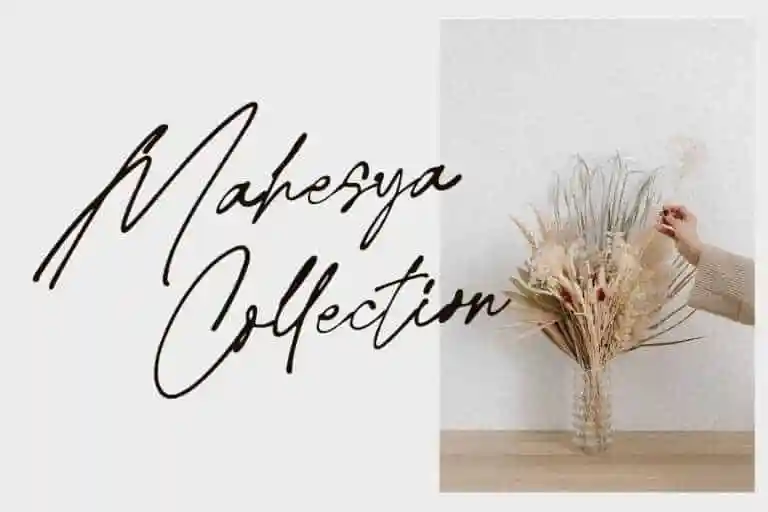
Belandia Signature Script Font – Download Grátis
A Belandia Signature Script Font é uma elegante tipografia escrita a mão que traz uma sensação natural e envolvente para qualquer projeto. Esta fonte perfeita tanto para assinaturas quanto para design de marca, logotipos e materiais promocionais, oferece um toque sofisticado aos seus trabalhos. Suas curvas fluidas e detalhes delicados são ideais para criar mensagens impactantes em estilos como postagem, web design e impressões publicitárias. Com uma aparência que não só combina bem com designs modernos, mas também oferece um toque clássico aos elementos mais tradicionais de seu trabalho. A Belandia Signature Script Font é a escolha perfeita para quem busca uma maneira refinada e única de expressar suas ideias através da fonte.